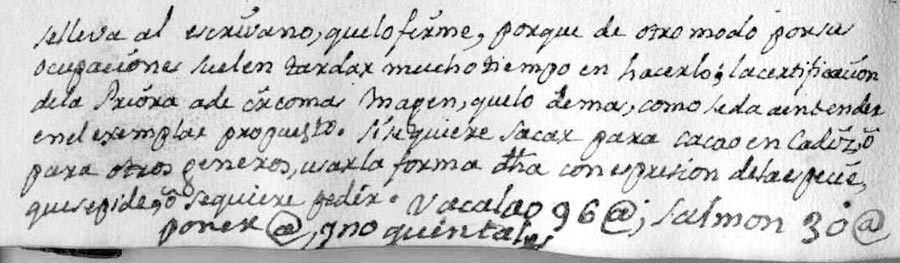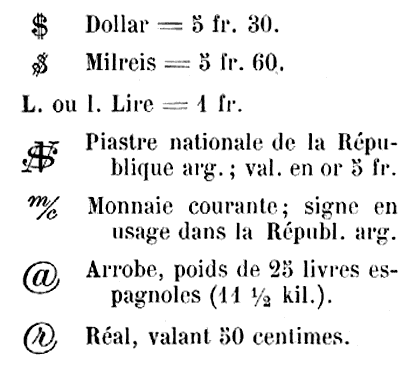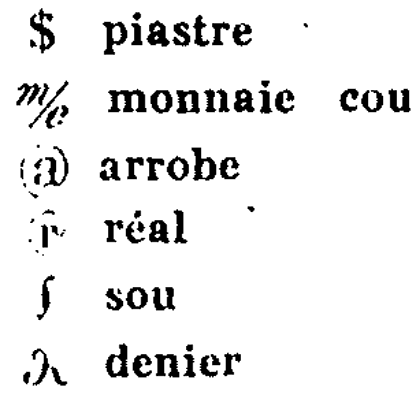
Arrobase ou Arrobe | l’origine du signe @ [at] (reloaded)
J’ai trouvé cette étude des plus complètes sur le site de http://hapax.qc.ca/ . Je prie les auteurs de ce billet de m’excuser car j’ai fait un petit copier coller où j’ai essayé un peu de remettre leur texte en ordre de lecture. Cela dit je trouve vraiment intéressant de rappeler que ce signe ‘@’ nous vient du XVe siècle. Preuve s’il en faut qu’Internet depuis le début fait référence à Gutenberg. En ce sens les administrateurs du web ont repris la tradition moderne des acteurs de la photocomposition d’utiliser la terminologie typographique établie de longue date. Le débat est ouvert, n’hésitez pas à poster vos commentaires.
Pourquoi l’ISO/CEI 10646 appelle-t-elle le signe @ une arrobe ?
Résumé: pour les gens pressés
Parce que c’est le nom traditionnel français de ce caractère, comme l’attestent plusieurs sources typographiques.
L’arrobe — une mesure de poids
L’arrobe est un terme bien attesté en français, il désigne une unité de poids espagnole (cf. le Trésor de la langue française informatisé) :
AROBE, ARROBA, subst. fém.
Ancienne mesure de poids (variant de 11 à 15 kg) et de capacité (valant de 10 à 16 litres), encore usitée en Espagne, au Portugal et dans plusieurs pays d’Amérique latine.
PRONONCIATION ET ORTHOGRAPHE
1. Forme phon. : [aR?b].
2. Forme graphique. : Robert, s.v. arobe avec un seul r renvoie à arrobe avec 2 r., Larousse encyclopédique enregistre parallèlement arobe, arrobe ou arroba; Quillet 1965 arrobe ou arobe.
3. Histoire : arrobe dans Dictionnaires de l’Académie. 1798-1878, Littré arroba ou arobe dans Complément du dictionnaire de l’Académie de 1842; arobe ou arrobe dans Bescherelle 1845, Guérin 1892 et Petit Larousse 1906; aroba ou arroba dans Larousse du XIXe siècle et Nouveau Larousse illustré.
Étymologie et Histoire
Première attestation : en 1555, métrologie arrobe « mesure espagnole de poids » (J. POLEUR, traducteur de l’Histoire naturelle et générale des Indes… de l’Espagnol Oviedo, fo 45 vo ds R. ARVEILLER, Fr. mod., t. 33, p. 300. : « les navires vont en Espagne chargés de sucre : car l’Arrobe vault icy un ducat ou moins, et est fort bon »;
Emprunté à l’espagnol arroba « mesure de poids », attesté dep. 1088 (sous la forme arrobo; arroa en 1194, arroba en 1219, d’après COR.) et qui avait aussi le sens 2 (cf. 1607, C. OUDIN, Tesoro de las dos lenguas francesa y española ds GILI t. 1). Le fait que le mot apparaît en français. dans un texte traduit de l’espagnol confirme cette étymologie. L’espagnol arroba est lui-même emprunté à l’arabe. al rub’ « le quart » (v. FEW t. 19, s.v. rub’).
Origine du symbole @
Selon la publication « Ligatures, typographie et informatique », Jacques André, Adolf Wild, rapport de recherche n°2429, décembre 1994, INRIA :
Le nom le plus fréquemment employé est « arobas ». Ce nom vient d’une confusion que nous expliquons de la façon suivante: les traducteurs qui ont voulu faire imprimer des manuels techniques où apparaissait pour la première fois ce signe ont du s’adresser à un imprimeur qui leur aura sorti un catalogue de fondeurs français. On y voit effectivement un caractère qui a à peu près la même graphie que @, qui s’appele arobas, mais qui correspond à quelque chose de complètement différent : c’est le symbole d’une ancienne unité de poids et de capacité encore usitée en Espagne et au Portugal (arroba, équivalent à 12 à 15 kg ou 10 à 16 l), dont le vrai nom français est d’ailleurs arrobe ou arobe. Le mot provient de l’arabe ar-roub signifiant « le quart ».
L’@ sert à noter l’arrobe
Le signe @ sert depuis des siècles à représenter l’arrobe dans les documents espagnols comme l’atteste le document ci-dessus écrit en 1775.
Exemples de @ utilisés pour désigner l’arrobe (1775)
Exemples de @ utilisés comme abréviation de l’arrobe (1775)
Extrait d’un cahier d’anecdotes du couvent de l’Ordre des religieuses déchaussées de la Très Sainte-Trinité, fondé en 1598 à La Roda, lieu-dit de la province d’Albacete en Castille — collection de l’auteur.
La 12e édition du Diccionario de la lengua castellana de la Real Aca­demia Española comprend une série d’abréviations courantes parmi lesquelles on retrouve « @ arroba, @@ arrobas ». L’usage devait être assez commun puisque ces abréviations se retrouvent dans l’Enci­clo­pedia Espasa de 1909.
Arrobe — le nom français du signe @
Jean-Pierre Lacroux signalait dans le Vademecum du typographe de Dumont : arrobe dans la composition française et faisait remarquer :
Et y a encore des experts pour prétendre que l’arrobe espagnole n’a aucun rapport avec @
Le symbole du réal est très intéressant. J’attends avec impatience l’experte explication de l’arabesque par un accent grave…
Dans une autre communication, le regretté Jean-Pierre Lacroux nous faisait parvenir l’image ci-dessous et ce commentaire :
Tiens, en voici une, extraite de la Composition typographique (1948) d’Henri Leduc. Elle est intéressante, car c’est un bricolage qui montre que ce caractère est absent des polices françaises MAIS qu’il est indispensable de le reproduire dans un manuel de composition… ailleurs que dans un chapitre consacré à la composition de l’espagnol…
Arrobe dans composition française
L’ISO/CEI 10646 utilise le mot arrobe
Par rapport à la version française de l’ISO 8859-1, la version française de l’ISO/CEI 10646 a rétabli le nom typographique traditionnel français de plusieurs caractères. Outre le nom d’arrobe, préféré au « à commercial » de l’ISO 8859-1, l’ISO/CEI 10646 nomme